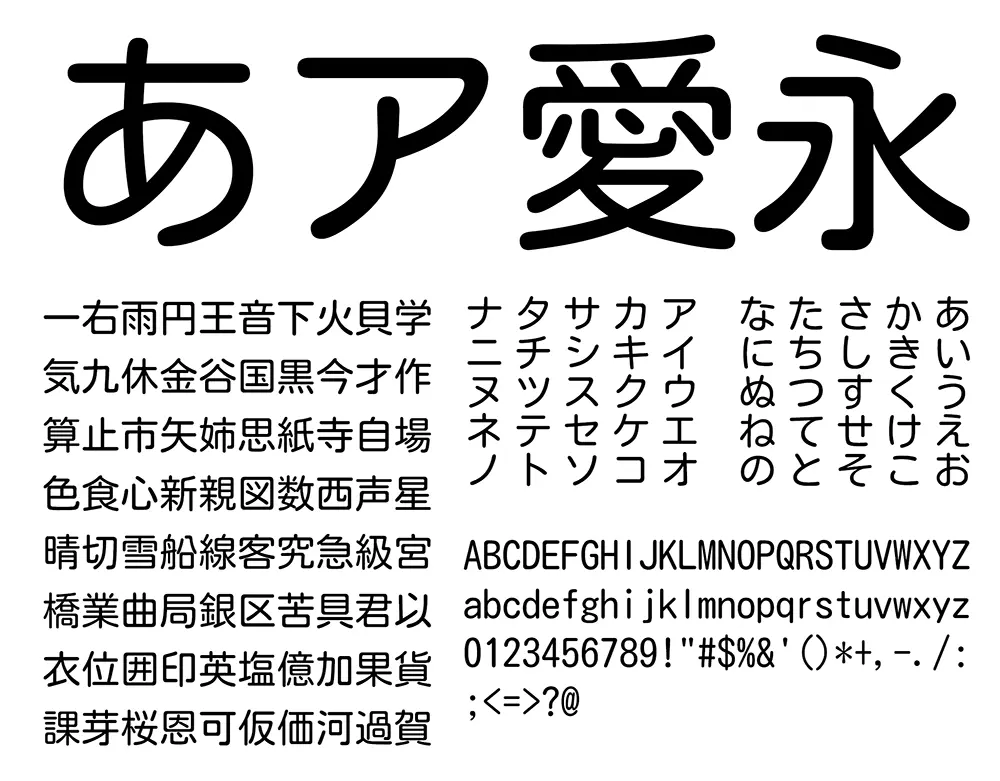
小杉圓體(英文名:Kosugi Maru)是一種哥特式圓角設計,筆畫對比度低,採用等寬字體,末端為圓形。該字體最初由MOTOYA開發,並在Apache許可證下為Android平臺發佈,基於20世紀50年代的設計。它旨在追求美觀和可讀性,並喚起人們對日本雪松的聯想,這些雪松有直而粗的樹幹和樹枝。最初以“MotoyaLMaru W3 mono”的名稱提供,現在以Kosugi Maru的名稱提供。
Kosugi Maru is a Gothic Rounded design, with low stroke contrast and monospaced metrics, and rounded terminals. Initially developed by MOTOYA and released for the Android platform under the Apache license, the typeface is based on a design from the 1950s. It aims for beauty and readability, and evokes the Japanese cedar trees that have straight and thick trunks and branches. Originally available as "MotoyaLMaru W3 mono", it is now available under the name Kosugi Maru.